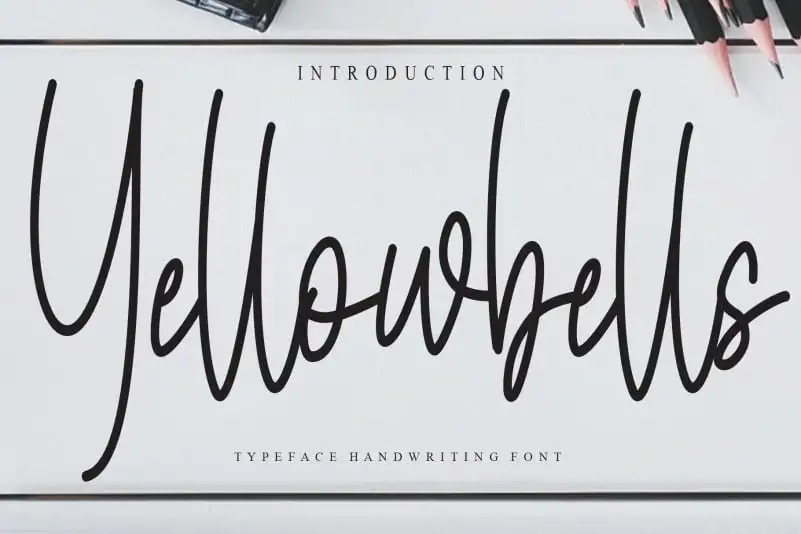
Descubra a autêntica essência da escrita manuscrita com a Yellowbells Handwritten Font. Esta elegante fonte é ideal para aqueles que buscam uma experiência única e especial, trazendo um toque pessoal aos seus projetos digitais. Com sua disposição delicada e detalhes cuidadosamente criados, ela oferece um tom suave e encantador, perfeito para textos de destaque ou pequenos detalhes. Esta fonte foi criada pelo designer creativletter para aqueles que valorizam a essência da escrita manuscrita, oferecendo uma opção diferenciada em sua categoria de letras cursivas. Seja você um designer gráfico, um escritor ou mesmo apenas alguém buscando uma maneira especial de expressar seu estilo pessoal, a Yellowbells Handwritten Font está aqui para te ajudar a fazer isso.